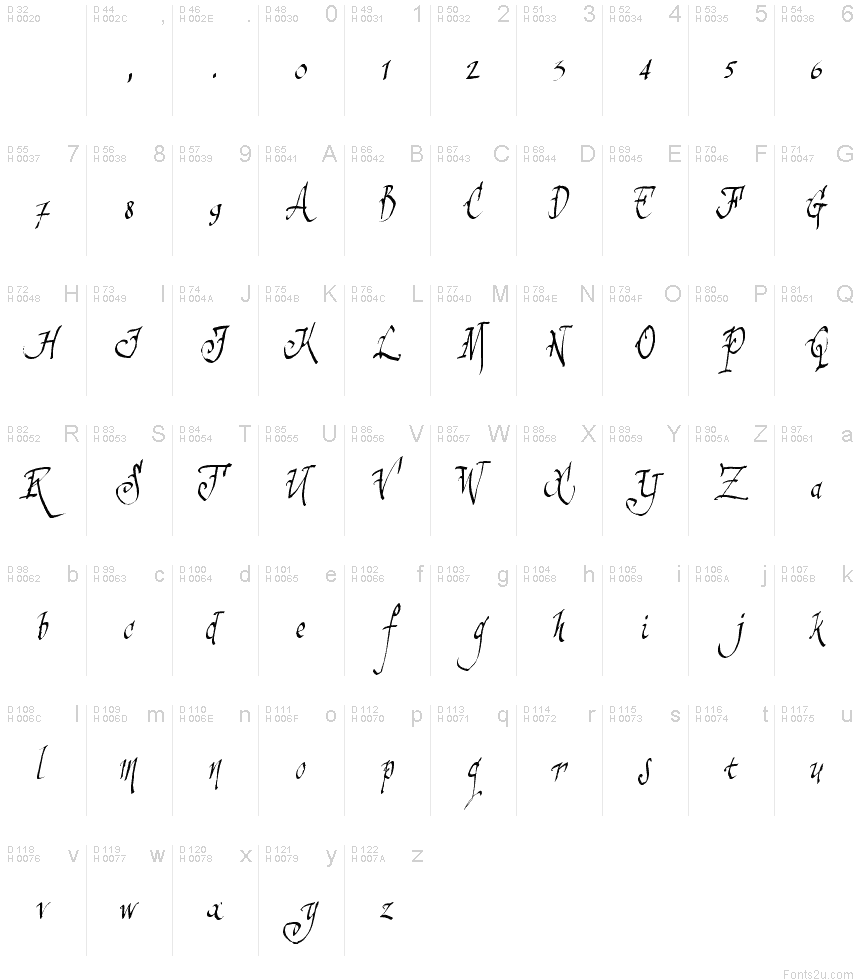
sinisterSam 字体
sinisterSam
JOEBOB Graphics
JJW van der Ham
J O E B O B graphics 推出的 Sinister Sam 是一款免费的手写脚本字体,带有哥特式童话般的狡黠氛围。字母采用了修长的卷曲笔画和尖锐的收尾,让整行文字带有一种诡异感,而柔和的笔触动作又使其不显僵硬或呆板。
它非常适合恐怖电影海报、万圣节派对用品、惊悚小说封面、神秘的店铺招牌以及需要戏剧性而非喧嚣效果的标题卡。在短标题、章节开头或名称和首字母组合中使用它,那些带钩的曲线和匕首般的结尾将能发挥出色的视觉效果。